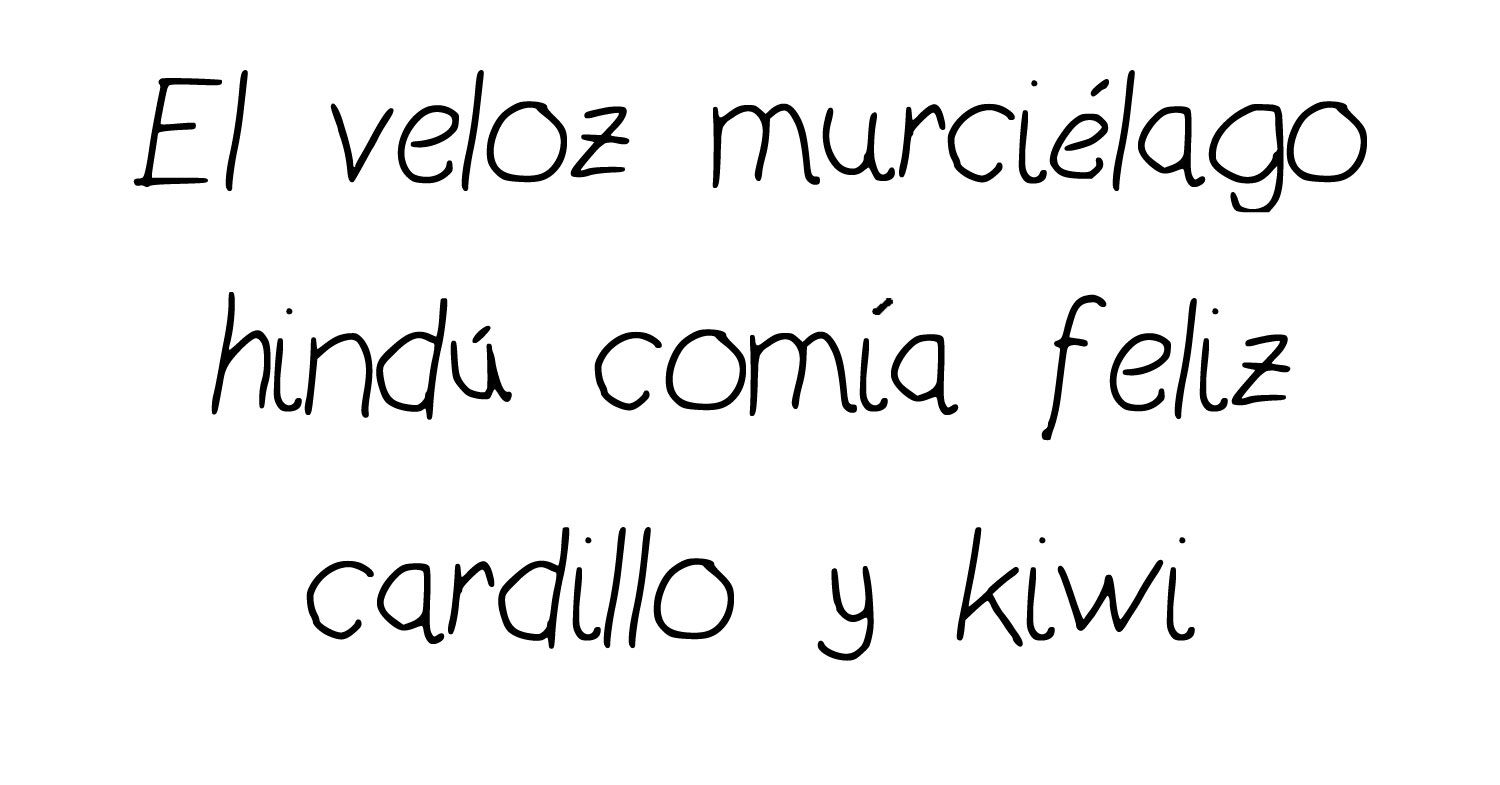
Convierte tu letra manuscrita en tipografía
Esta web te permite crear una tipografía funcional a partir de la escritura de tu puño y letra, de manera fácil y gratuita
Con la llegada de los ordenadores a nuestras vidas la escritura manual ha quedado relegada, en muchas ocasiones, a notas cortas de usar y tirar y uso interno que algunos, incluso, prefieren escribir en su teléfono móvil. Hemos perdido la práctica de escribir de nuestro puño y letra y se ha perdido también la magia de recibir cartas o documentos escritos a mano. Myscriptfont es un software online y gratuito que pretende recuperar la letra manuscrita convirtiendo nuestra escritura en una tipografía que puede usarse en cualquier ordenador.
Convertir nuestra escritura en tipografía es tan sencillo como descargar la plantilla, en formato pdf o png, y practicar nuestra caligrafía sobre ella. Puedes imprimirla y escribir con un rotulador grueso sobre el papel o hacerlo directamente en el ordenador con una tableta gráfica. Una vez completados todos los glifos sólo hay que subir el archivo a la web.
El sistema de Myscriptsfont nos permite elegir el nombre de nuestra tipografía y si preferimos obtenerla en formato OTF o TTF. Pulsando 'start' veremos una muestra de texto con la tipografía creada y podremos descargar e instalar el archivo en nuestro ordenador para usarlo en nuestros programas habituales de edición. La tipografía resultante está completamente libre de copyright y puedes hacer lo que quieras con ella.
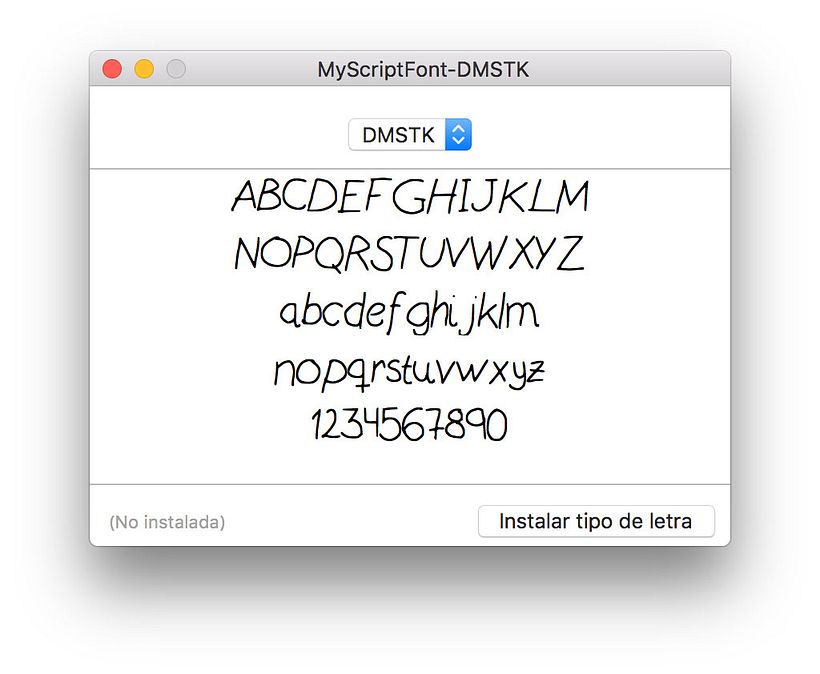
Evidentemente, las tipografías creadas con Myscriptfont no son perfectas en cuanto a diseño, pero es una buena manera de incluir nuestro toque personal en nuestros proyectos y además es gratis.